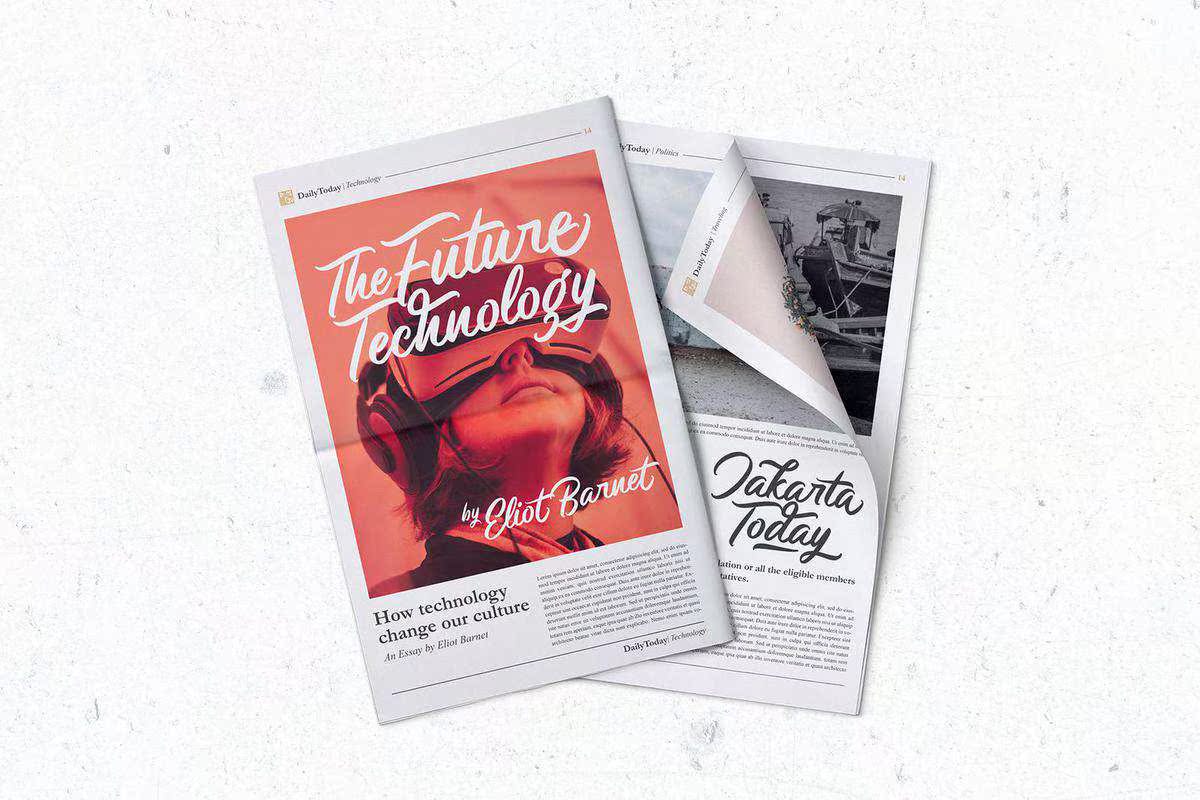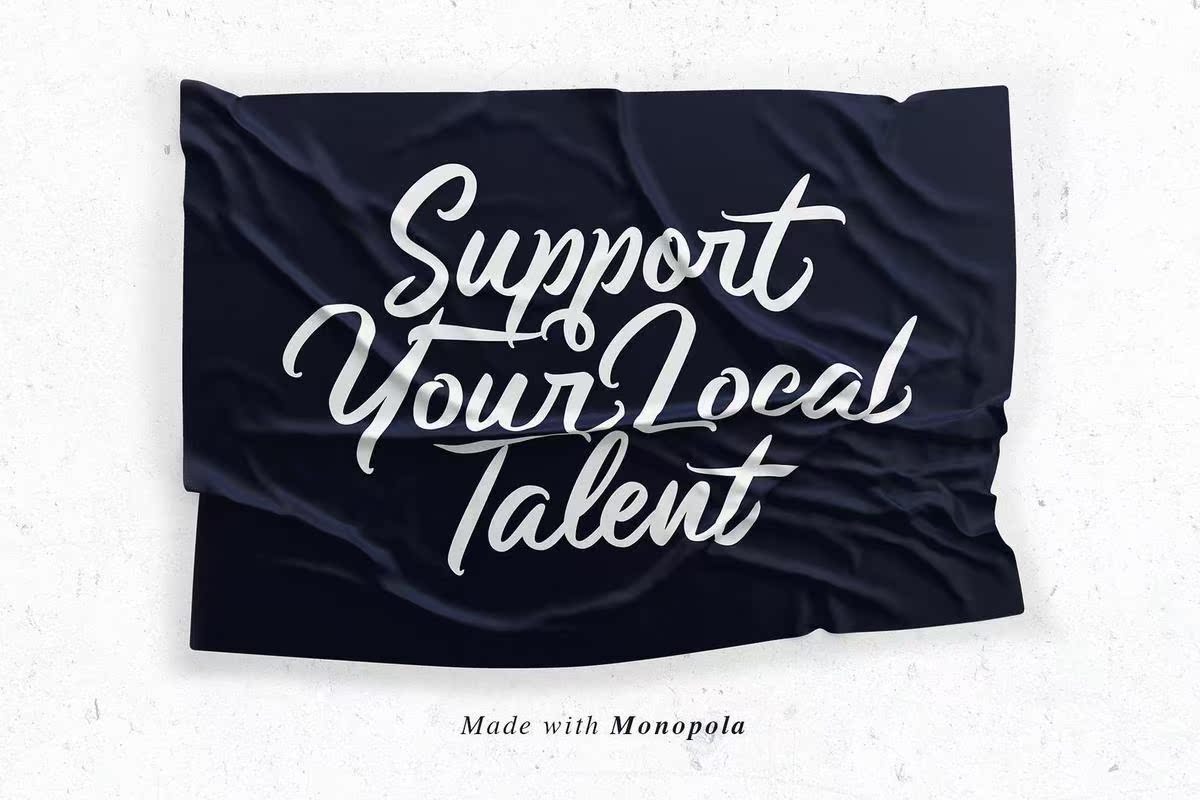
MonopolisaCasualScriptFontInspired by Popultures Andorbanfashion。此Fonts适用于您的下一个创作项目,如徽标、打印报价、邀请函、卡片、产品包装、标题、信头、海报、装置标志、标签等。MonopolisaCasualScriptFontInspired by Popultures Andorbanfashion。此Fonts适用于您的下一个创作项目,如徽标,打印的报价单、邀请函、卡片、产品包装、标题、信头、海报、服装标志、标签等。